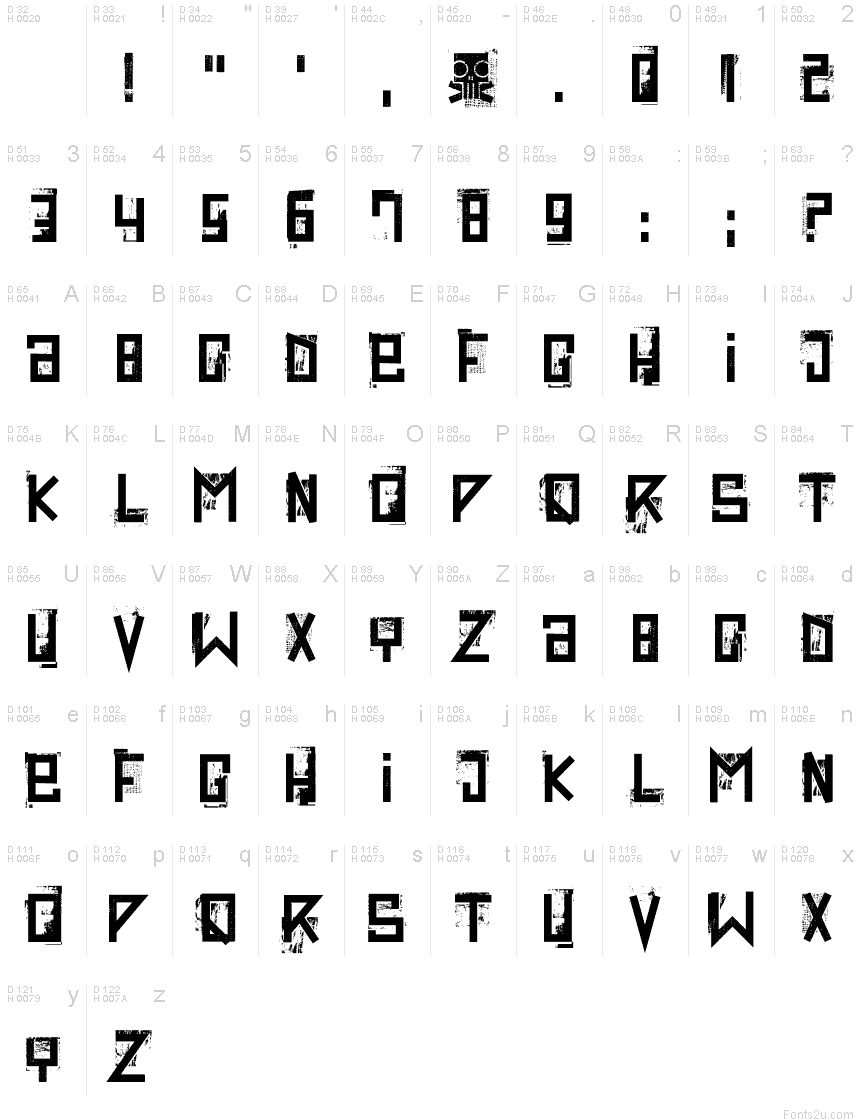
Extravaganza to darmowy krój displayowy o estetyce techno i zniekształconej formie. Ciężkie, blokowe kształty zderzają się z poszarpanymi przekątnymi, a surowa, erodowana tekstura przegryza się przez litery niczym szum na uszkodzonym ekranie. Całość balansuje między graffiti a glitchem, z grubymi, nasyconymi atramentem pociągnięciami, które uderzają z mocą, pozostawiając za sobą ślad cyfrowego szumu.
Z Extravaganza Twoje nagłówki natychmiast zyskają klimat rave’owego plakatu lub menu z dystopijnej gry. Ten darmowy font świetnie sprawdzi się na plakatach koncertowych, okładkach albumów, w brandingach o tematyce hakerskiej czy cyber, grafice streetwearowej i odważnych tytułach w motion designie. Używaj go w dużym rozmiarze, aby uwydatnić zniszczone detale, a jako tekst pomocniczy dobierz prosty, geometryczny bezszeryfowy krój – dzięki temu chaos w głównym napisie będzie jeszcze bardziej widoczny.